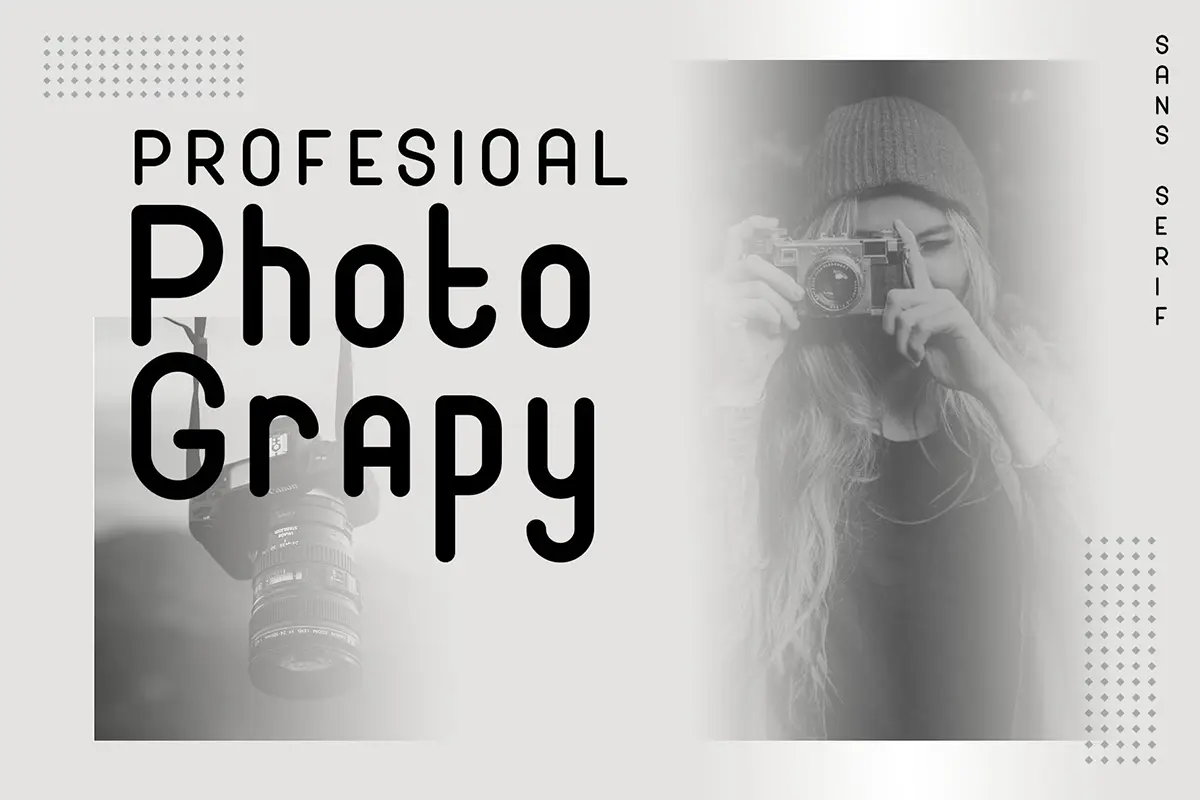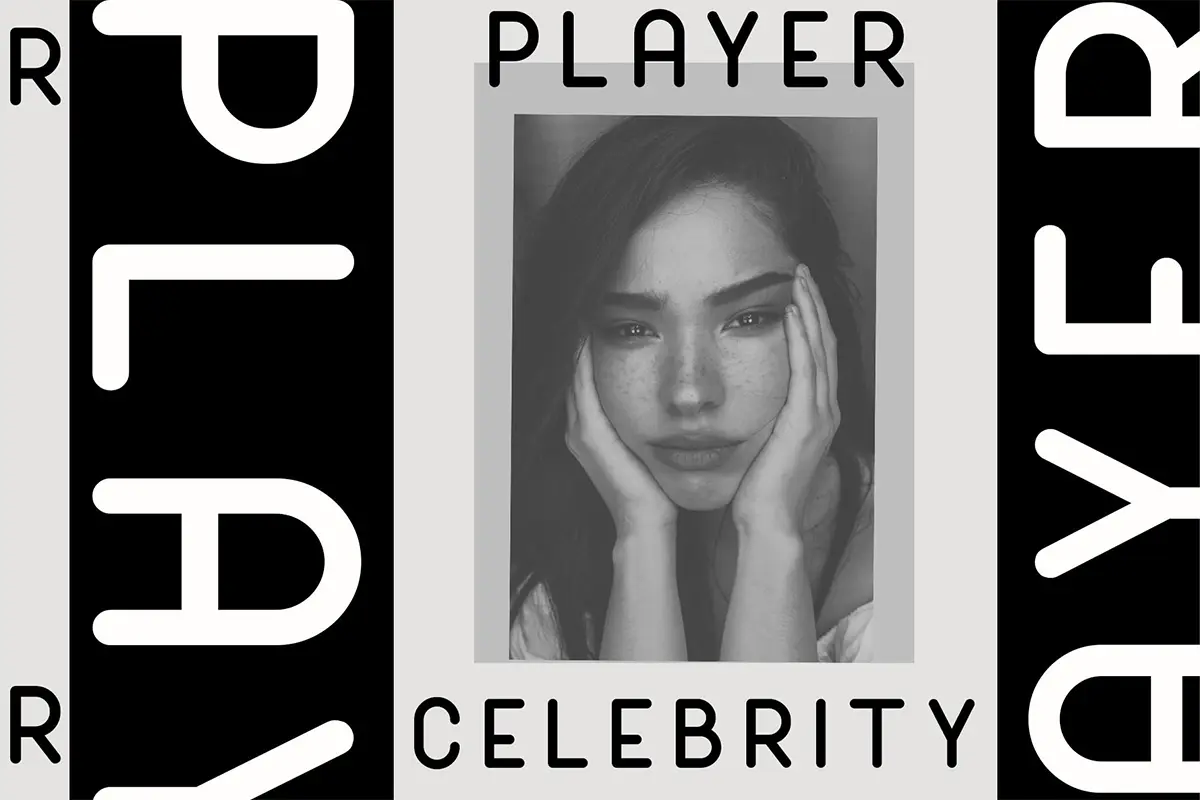
فونت سن سریف مدرن و چندمنظوره
فونت Halena یک فونت سن سریف مدرن، تمیز و انعطافپذیر است که برای طیف گستردهای از طراحیها مناسب است. سادگی و نظم در ساختار حروف باعث میشود این فونت بهراحتی در هر پروژهای بدرخشد و تبدیل به انتخاب همیشگی و مطمئن شما شود.
⭐ ویژگیهای محصول
- فونت سنسریف مدرن با طراحی ساده و حرفهای
- سبک تمیز و مینیمال مناسب برای انواع پروژهها
- قابلیت استفاده در طراحیهای چاپی و دیجیتال
- خوانایی بالا در اندازههای کوچک و بزرگ
- مناسب برای برندینگ، پوستر، وبسایت و رابط کاربری
🎯 موارد استفاده
- طراحی لوگوهای مدرن و مینیمال
- ساخت پوسترها و بنرهای تبلیغاتی
- طراحی رابط کاربری (UI) و صفحات وب
- استفاده در اسناد رسمی و ارائههای حرفهای
- افزودن به پورتفولیو برای نمایش سبکهای تمیز و کاربردی